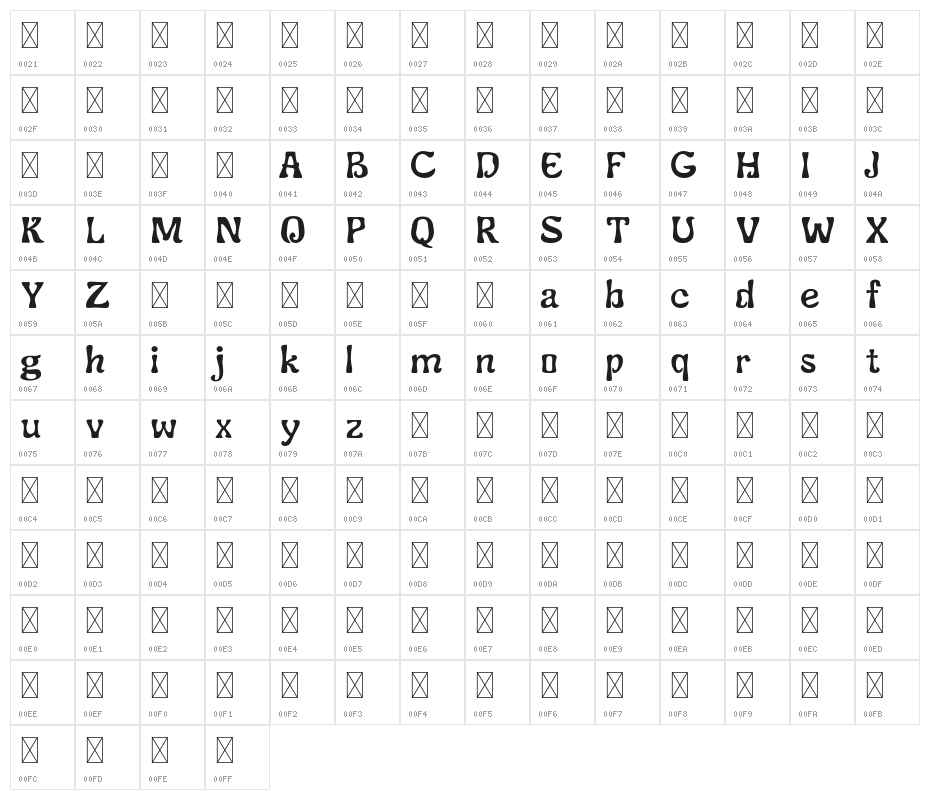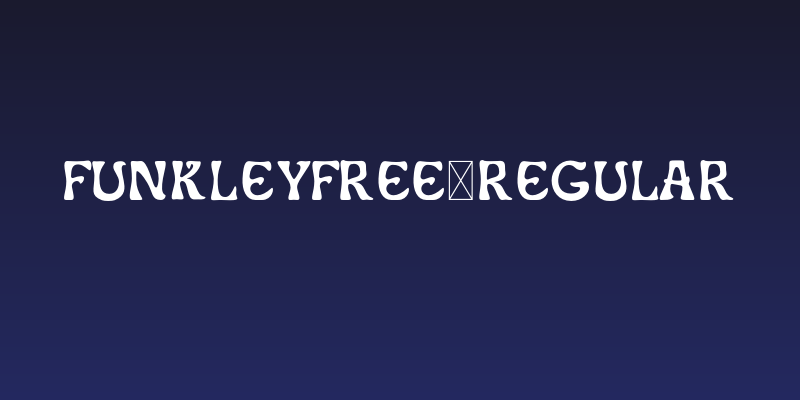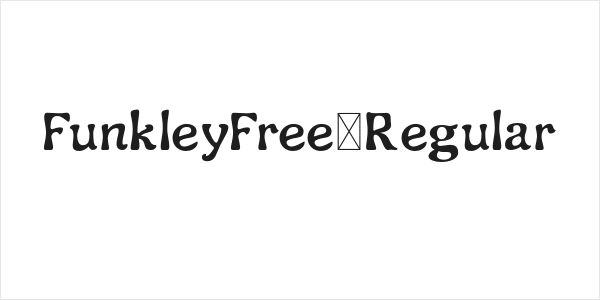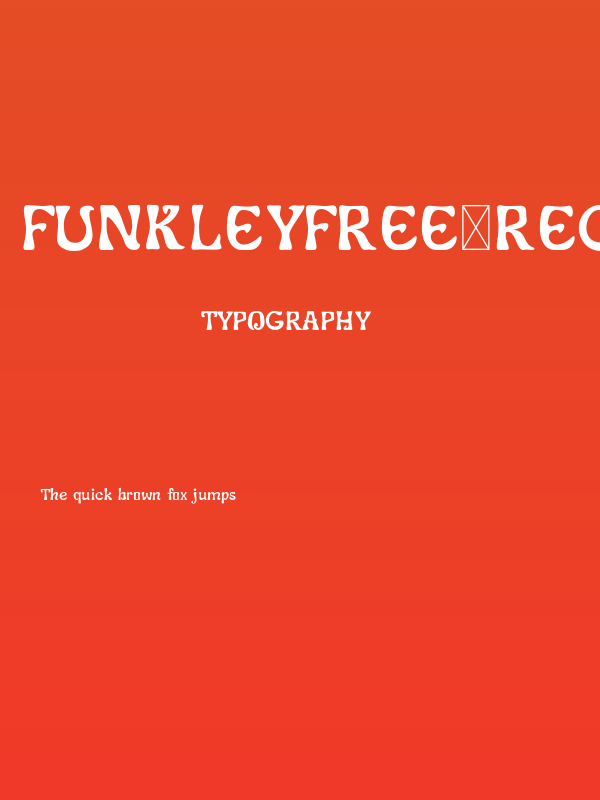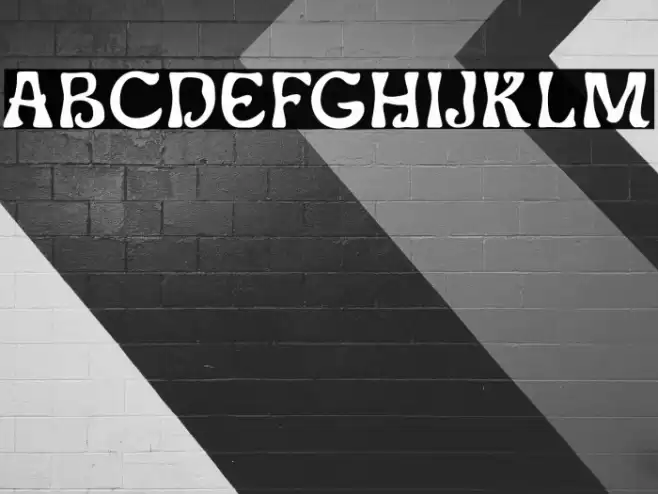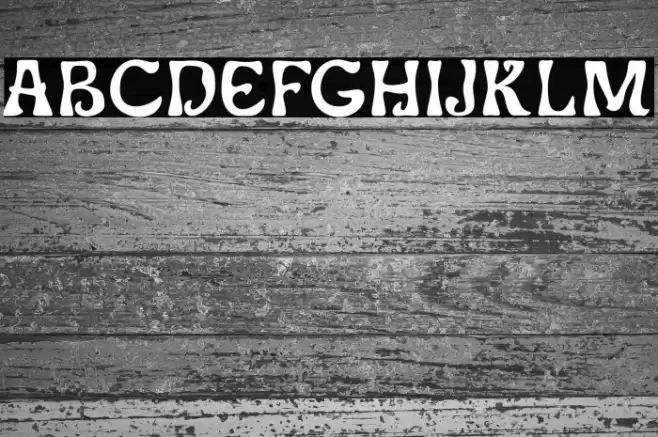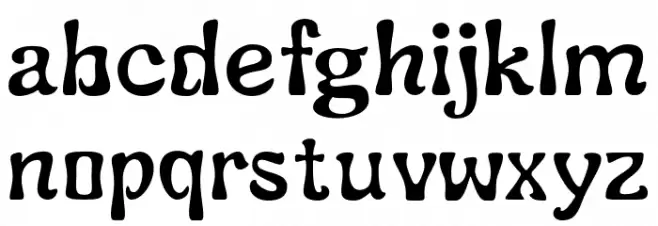
FunkleyFree-Regular Font
Fonts by Craft Supply Co.
| समग्र शैली | Whimsical, Artistic, Playful |
| उपयोग का मामला | Logos, Posters, Invitations |
| सुझाए गए प्रोजेक्ट | Ideal for children's books, creative posters, playful branding, and artistic invitations. |